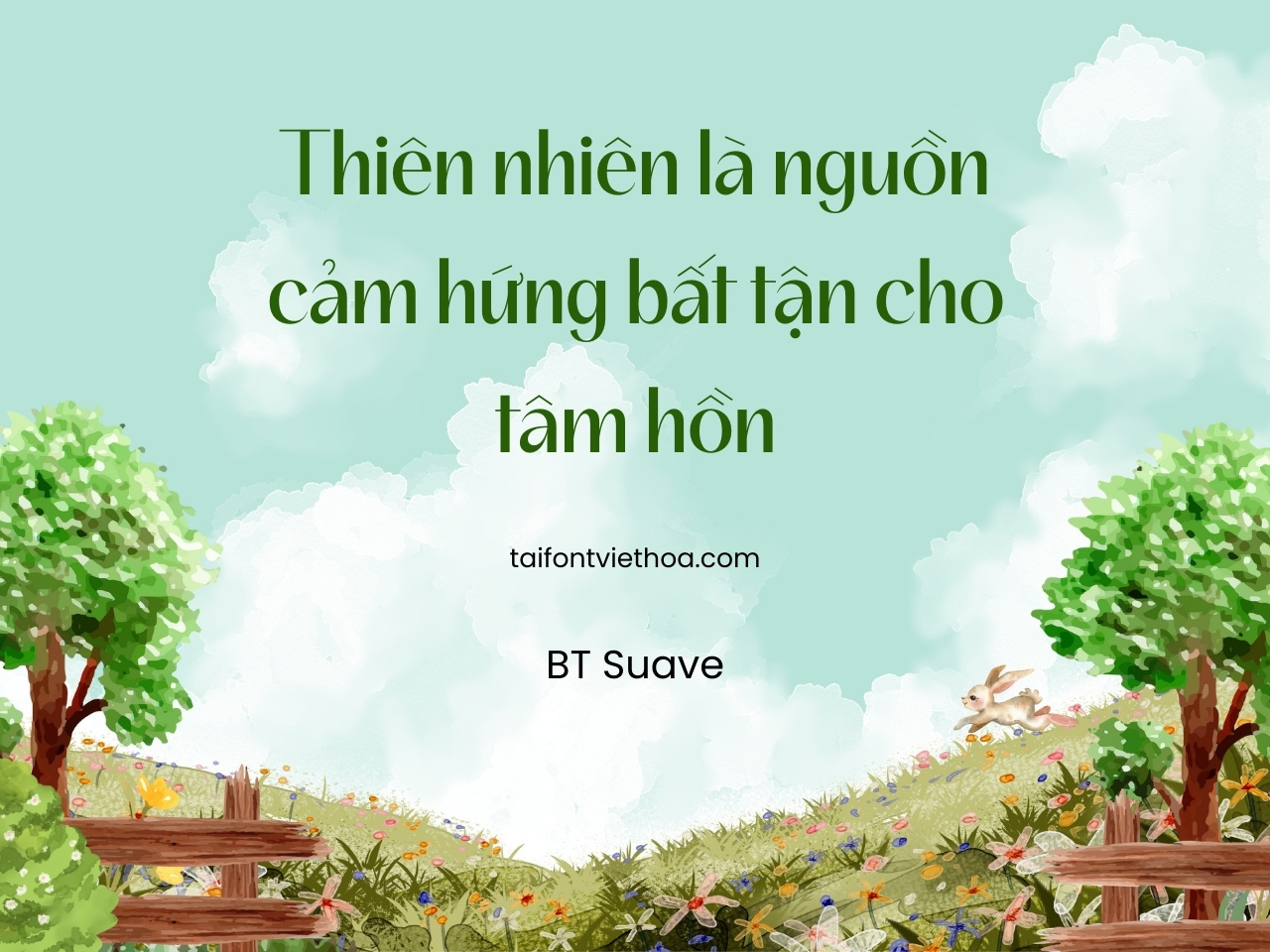
Giới thiệu về font BT Suave và phiên bản Việt hóa
BT Suave là một bộ font sans-serif kết hợp display hiện đại, được thiết kế bởi Beautype Studio – một studio thiết kế font quốc tế nổi bật với các bộ chữ mang tính ứng dụng cao. BT Suave gây ấn tượng nhờ đường nét gọn gàng, sắc sảo nhưng vẫn giữ được sự mềm mại trong các chi tiết uốn lượn, tạo cảm giác thân thiện và chuyên nghiệp. Font đã được Việt hóa hoàn chỉnh bởi chính Beautype Studio, hỗ trợ đầy đủ tiếng Việt chuẩn Unicode và hơn 75 ngôn ngữ quốc tế sử dụng bảng chữ Latin mở rộng.
Đặc điểm hình thái thiết kế và lĩnh vực ứng dụng
BT Suave mang cấu trúc chữ sans-serif hiện đại với nét cắt chính xác và độ dày đồng đều. Một số glyphs đặc biệt có thiết kế uốn lượn nhẹ ở các cạnh tạo điểm nhấn tinh tế. Font có tính dễ đọc cao, tỉ lệ ký tự cân đối, giúp tối ưu trải nghiệm thị giác trên các nền tảng số lẫn in ấn.
BT Suave phù hợp với nhiều ngành nghề như giáo dục, quảng cáo, công nghệ, bất động sản hoặc mỹ phẩm. Ngoài ra, nhờ nét đẹp tinh tế và dễ nhận diện, font cũng được áp dụng rộng rãi trong các thiết kế banner dịp lễ, thiệp Valentine, sinh nhật hoặc các chiến dịch marketing mùa xuân – nơi cần thể hiện sự hiện đại mà vẫn giữ được tính ấm áp, gần gũi.